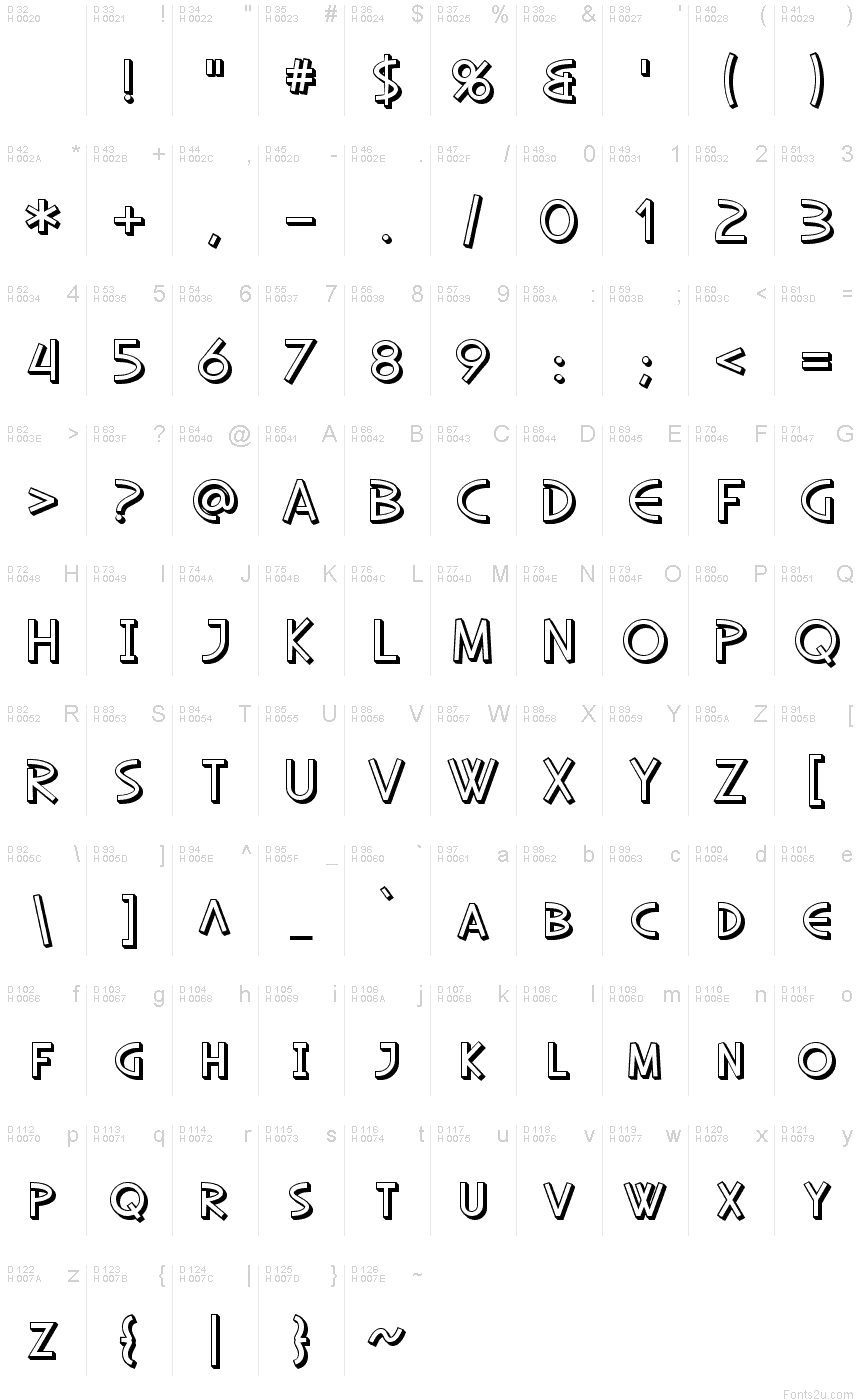
SF Diego Sans Shaded od ShyFoundry to darmowy, komiksowy krój displayowy z grubymi wersalikami, jasnym podświetleniem i blokowym cieniem, który nadaje literom charakter wycinanki lub plakatu z kreskówki. Alfabet łączy szerokie łuki z kwadratowymi narożnikami, dzięki czemu całość wygląda zabawnie, ale nie traci na wyrazistości, a powtarzający się cień nadaje stylowi graficznego, zdecydowanego charakteru.
Sprawdza się w okładkach książek dla dzieci, nagłówkach komiksów, zaproszeniach, plakatach i kreatywnych opakowaniach, gdzie wbudowany efekt cienia dodaje krótkim słowom dynamiki bez zbędnych dodatków. Jako darmowy font, świetnie nadaje się również do tytułów, monogramów i dużych inicjałów, gdy zależy Ci na żywym, retro klimacie ręcznie malowanych szyldów.
SF Diego Sans Shaded
ShyFoundry
Derek Vogelpohl